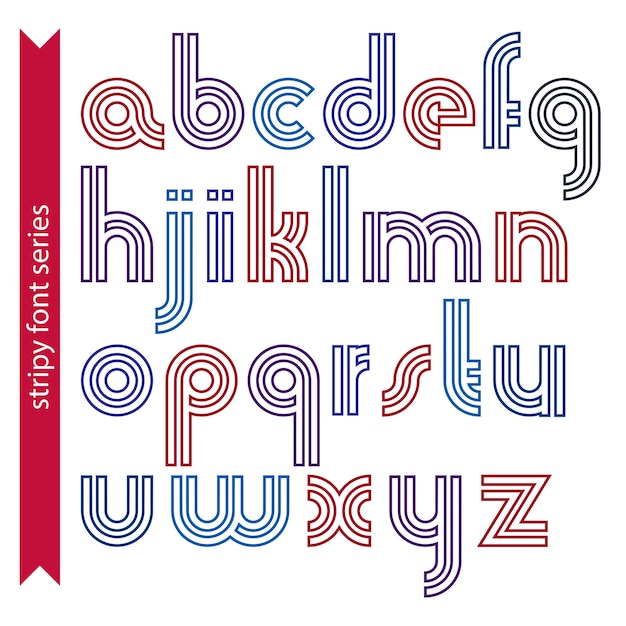
Набор векторных строчных букв диско-алфавита в стиле фанк. Модный шрифт, машинопись для использования при создании логотипа. Создан с использованием геометрических тройных полос.Набор векторных строчных букв диско-алфавита в стиле фанк. Модный шрифт, машинопись для использования при создании логотипа. Создан с использованием геометрических тройных полос.
Набор векторных строчных букв диско-алфавита в стиле фанк. Модный шрифт, машинопись для использования при создании логотипа. Создан с использованием геометрических тройных полос.